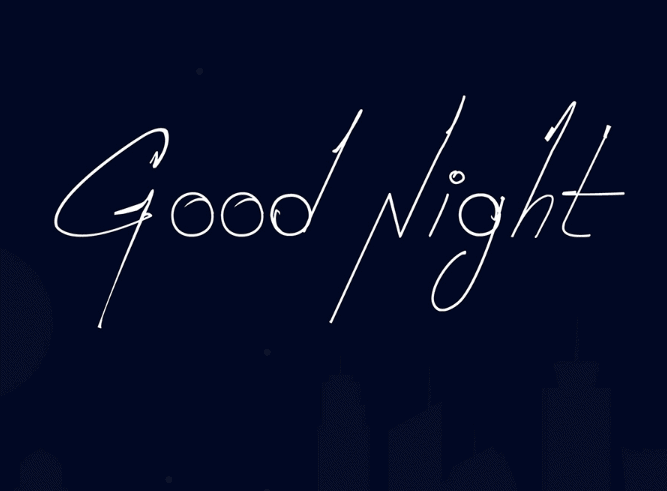
Good Night Font – Download Grátis
Aqui está uma descrição para a página de download da fonte ‘Good Night Font’ que segue as regras fornecidas: Uma fonte escrita à mão perfeita, apresentada aqui pela primeira vez. Good Night é um trabalho de Erick Molina, designer originário de Tijuana, México. Esta fonte foi criada especialmente para aqueles que desejam incorporar a aparência natural e pessoal do traçado ao seu design. Seja você um artista digital ou designer gráfico, Good Night oferece uma maneira simples e inovadora de alcançar este objetivo. Com o Good Night Font, você será percebido como alguém lendo os traços de outra pessoa em vez de apenas texto, criando um estilo único e autêntico. Esta fonte é ideal para aqueles que desejam adicionar uma personalidade única a seus projetos digitais ou impressos. Ainda não experimentou o poder da escrita à mão? Então Good Night Font pode ser seu primeiro passo para capturar esse sentimento único e transformá-lo em arte digital.